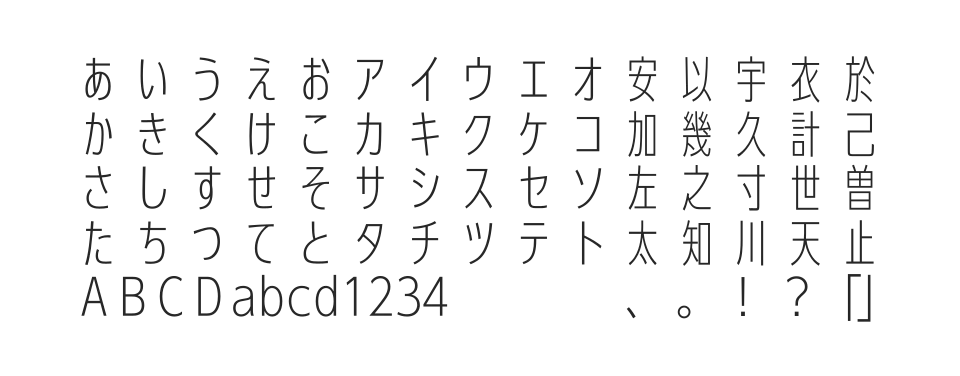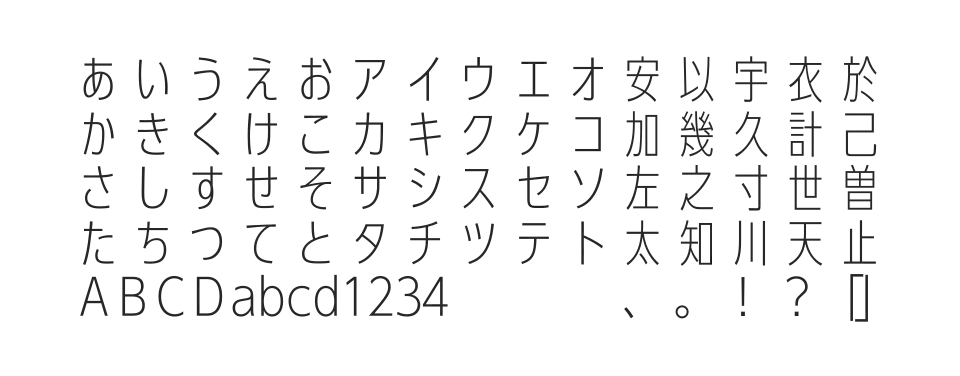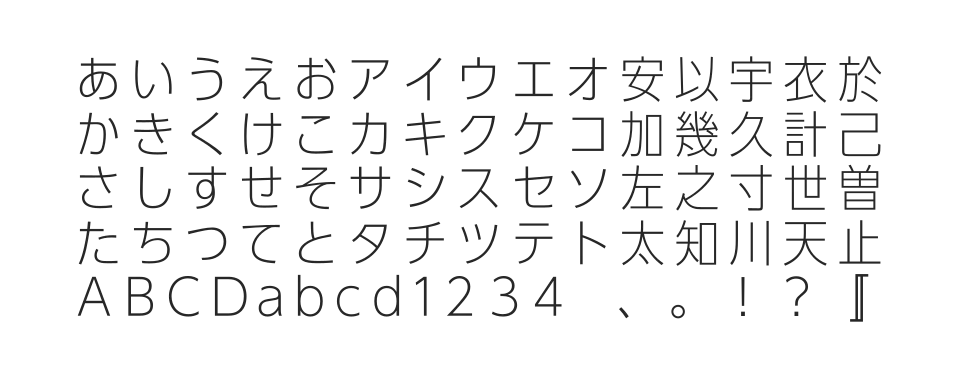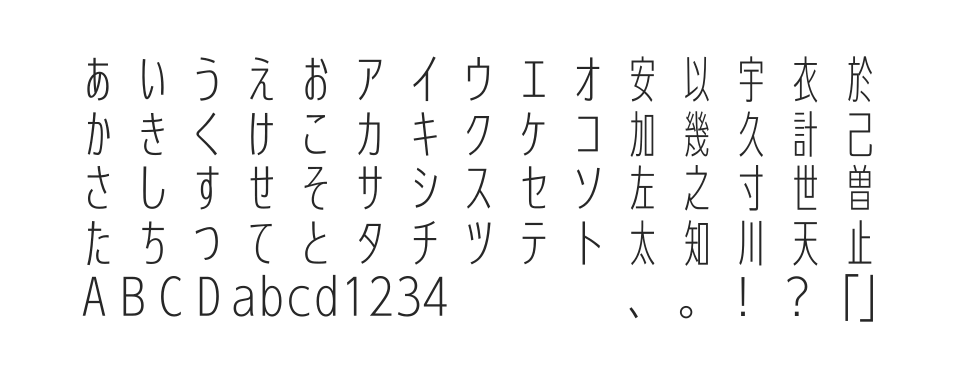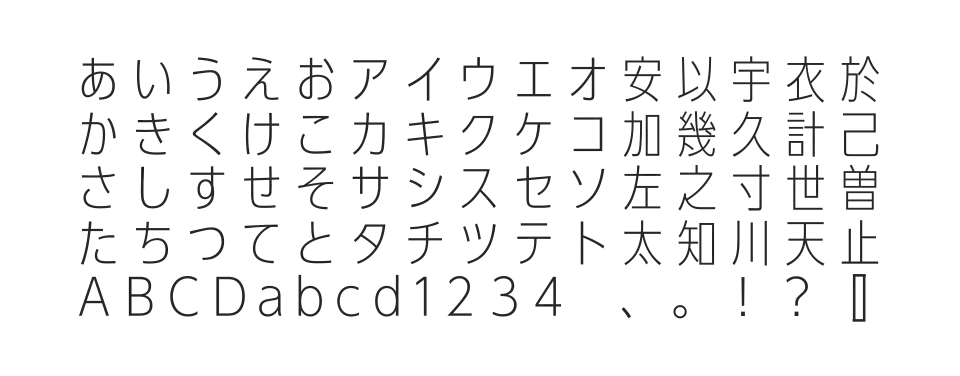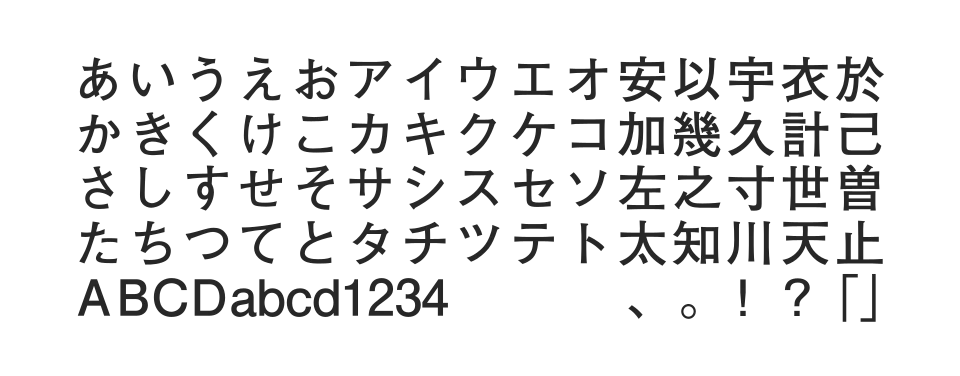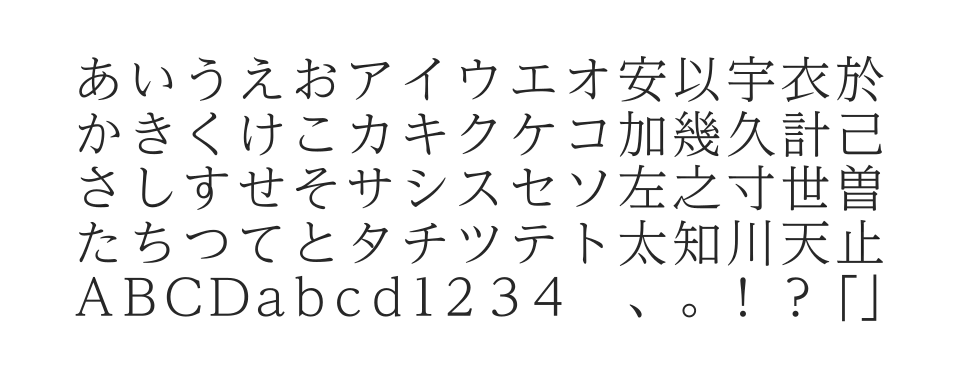
2021年リリースのモダンなゴシック体。シンプルかつクリーンな骨格で小さめの字面を採用し、従来のモダンゴシックとは異なる表情の組版が可能な現代的なフォント。
明朝体特有の細い横画にしっかりと太みをもたせたユニバーサルデザイン書体。視認性と可読性を重視し、縦組・横組どちらでも美しく並ぶ明朝体フォントです。
活字書体のデザインを忠実に引き継ぐゴシック体。オーソドックスなデザインと安定した字面で、用途を選ばず広範囲に使いやすいモリサワの定番フォントです。
限られたスペースでも高い可読性を保つコンデンス書体。UD新ゴをベースに長体率80%で最適化されたユニバーサルデザイン対応のゴシック体フォントです。
限られたスペースでも高い可読性を保つコンデンス書体。UD新ゴをベースに長体率50%で最適化されたユニバーサルデザイン対応のゴシック体フォントです。
限られたスペースでも高い可読性を保つコンデンス書体。UD新ゴをベースに長体率90%で最適化されたユニバーサルデザイン対応のゴシック体フォントです。
限られたスペースでも高い可読性を保つコンデンス書体。UD新ゴをベースに長体率70%で最適化されたユニバーサルデザイン対応のゴシック体フォントです。
UD新ゴをベースに展開したコンデンス(長体)書体です。限られたスペースでも可読性を保ちながらより多くの情報を表示できる60%コンデンス仕様。